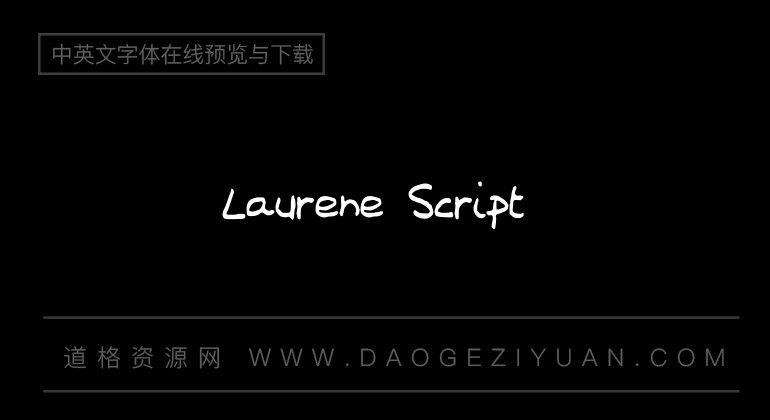
Laurene Script是一种花体手写字体,非常适合用于品牌标志、信头、海报、包装等设计项目中。它具有流畅、优美、优雅的笔画,能够带来浪漫、女性化的感觉,同时也有一定的现代感。 该字体的字形设计非常精细,每个字母都有独特的特点,每个字母之间的间距也很合理,使得整个字体看起来非常协调和平衡。 Laurene Script字体家族包含了常规、加粗、轻盈、斜体和粗斜体等不同版本,可以满足不同设计需求。该字体支持多种语言,包括中文、英文、法语、德语、西班牙语等,非常实用。 总之,Laurene Script字体是一种非常优美、流畅的手写字体,适合用于各种品牌设计和文化艺术领域。内容介绍
Laurene Script 是一款非常不错的手写艺术字体,具有很好的视觉感,适合于文化类的宣传设计、商业类品牌的广告和产品包装设计以及个性化文字排版等较多场景。